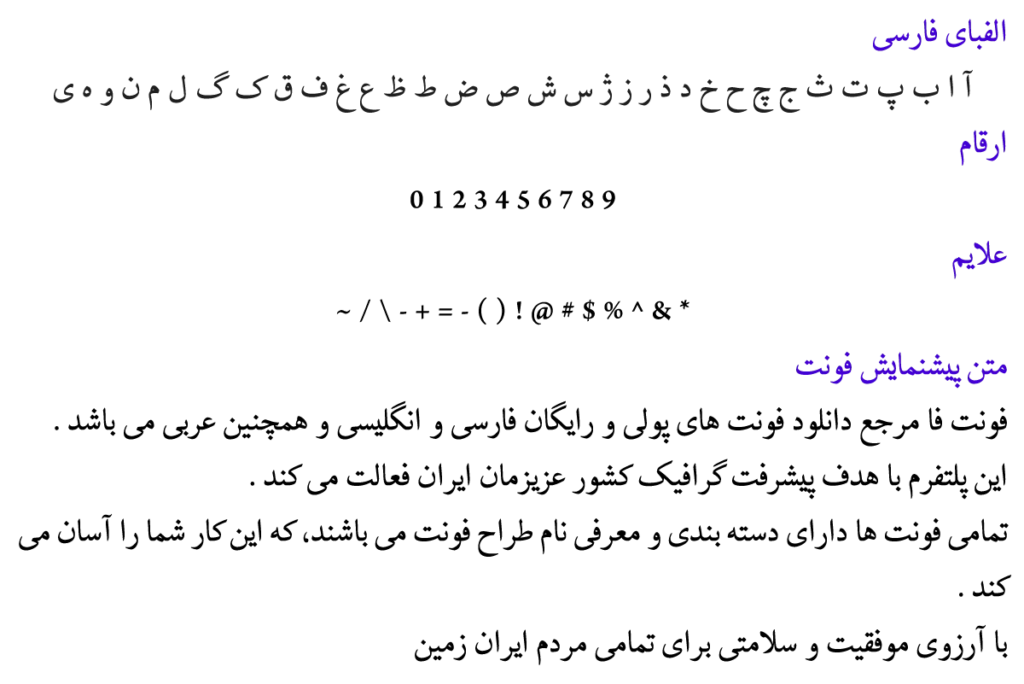
فونت فارسی ادوبی نسخ – Adobe Naskh
نوع فونت: فونت خوشنویسی
توضیحات و معرفی فونت ادوبی نسخ
فونت فارسی ادوبی نسخ ( Adobe Naskh ) از مجموعه فونت های آزاد می باشد، همچنین نوع فونت خوشنویسی می باشد.
فونت فوق العاده زیبای معرفی شده توسط محمد زهیر روحانی بازی طراحی و ساخته شده است.
این فونت، خطی است که در اوایل قرن سوم هجری قمری توسط ابن مقله شیرازی ابداع شد و در آغاز، هم پایه خط کوفی به شمار می رفت.
در تصویر زیر، شعر زیبای وطنم که با این تایپ فیس نگاشته شده است، قابل مشاهده است.